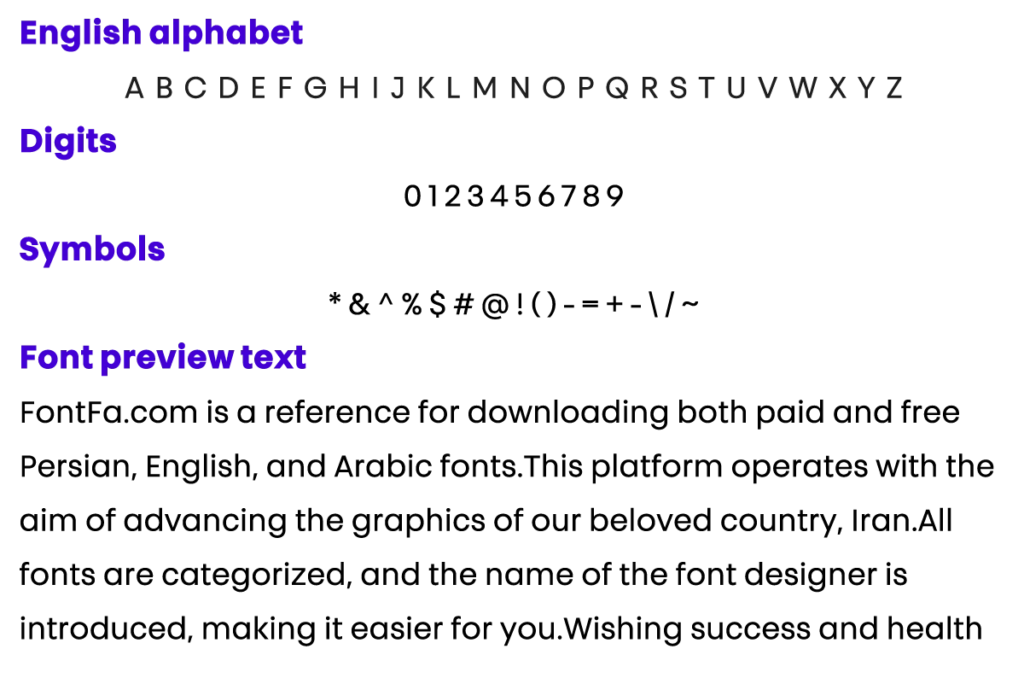
فونت انگلیسی Touche
نوع فونت: فونت متن و فونت هندسی
توضیحات و معرفی فونت Touche
فونت انگلیسی Touche ( Touche ) از مجموعه فونت های آزاد می باشد، همچنین نوع فونت متن و هندسی می باشد.
فونت فوق العاده زیبا و جذاب معرفی شده که توسط Indian Type Foundry در سال 2023 طراحی که دارای مجموعه های سبک شناختی متنوع و وزن های متغیر می باشد.
همچنین فونت Touche در 6 وزن پر رنگ و نیمه پر رنگ و سبک و متوسط و معمولی و کج است.
در لیست زیر می توانید وزن های این فونت فوق العاده زیبا را ببینید.
- Touche Bold
- Touche DemiBold
- Touche Light
- Touche Medium
- Touche Regular
- Touche Italic